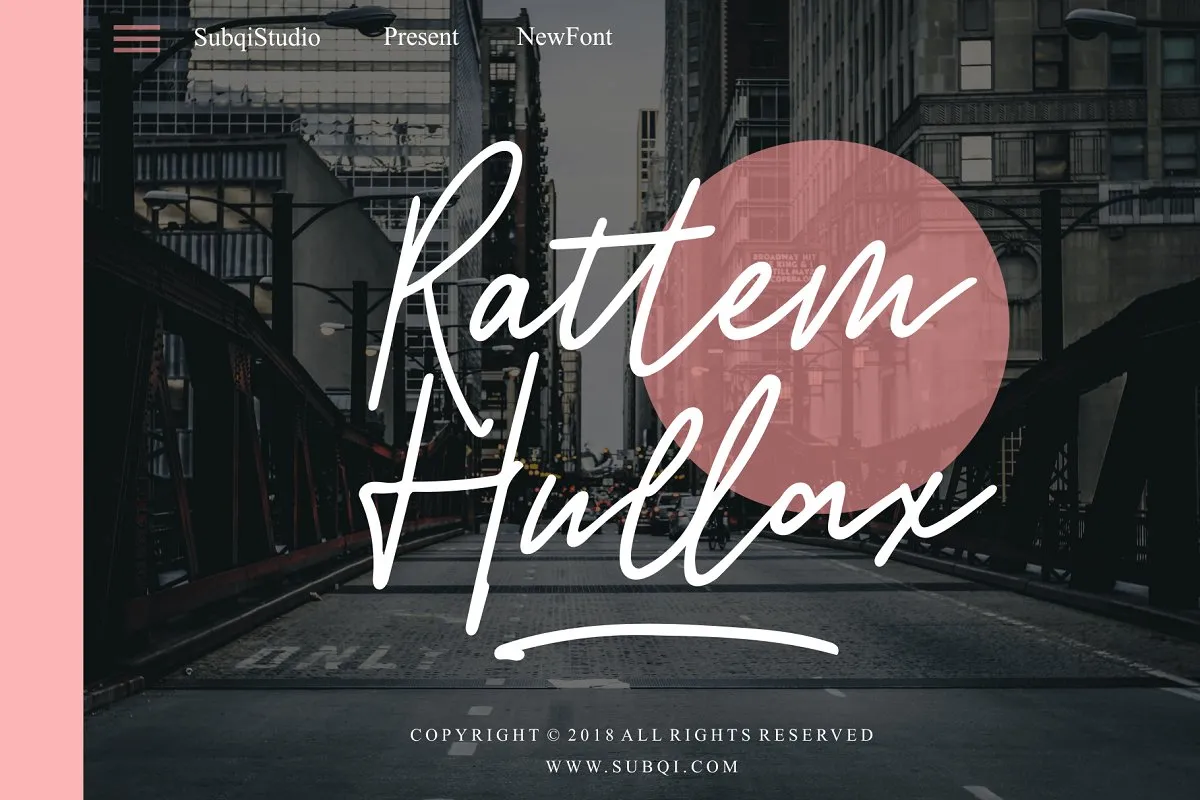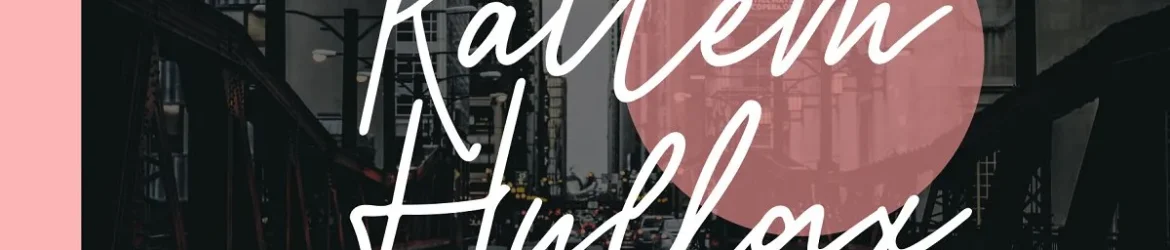
Rattem Hullax Signature Font – Download Grátis
A Ratem Hullax Signature é uma nova tipografia de assinatura criada para profissionais dedicados ao design que buscam um toque diferente na sua paleta. Introduzida por 24Design, esta font se destaca como a escolha perfeita para designers profissionais em busca de algo único e emocional. Rattem Hullax é uma tipografia de escrita feita à mão com caneta esferográfica, criando um toque orgânico que se integra perfeitamente às necessidades específicas do design. Este tipo de font foi projetada especificamente para logos femininos, cartas de casamento amáveis, postagens em blogs e até mesmo impressões publicitárias. A Ratem Hullax é uma fonte de escrita ideal para qualquer projeto que desejamos transmitir uma mensagem delicada ou elegante, proporcionando um acabamento único às suas criações.